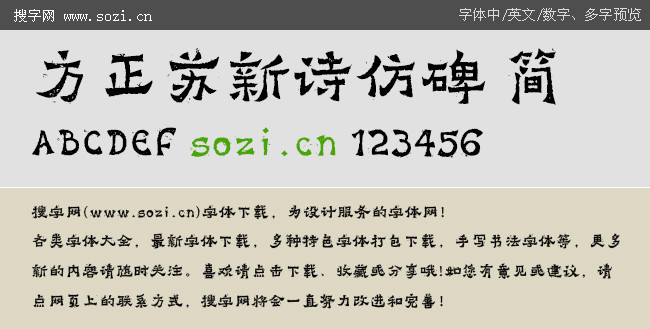
方正蘇新詩仿碑-簡
搜字網(wǎng)提供一款方正蘇新詩仿碑中文書法字體下載,方正蘇新詩仿碑爨是在標準小爨體增加了斑駁感的。字型來源于東晉《晉故振威將軍建寧大守爨府君墓碑》究其淵源,因?qū)匐`變時期的作品,體勢情趣、情態(tài)均在隸楷之間。奇姿異態(tài)、樸茂古厚、大巧若拙、率真硬朗、氣度高華、氣魄雄強。